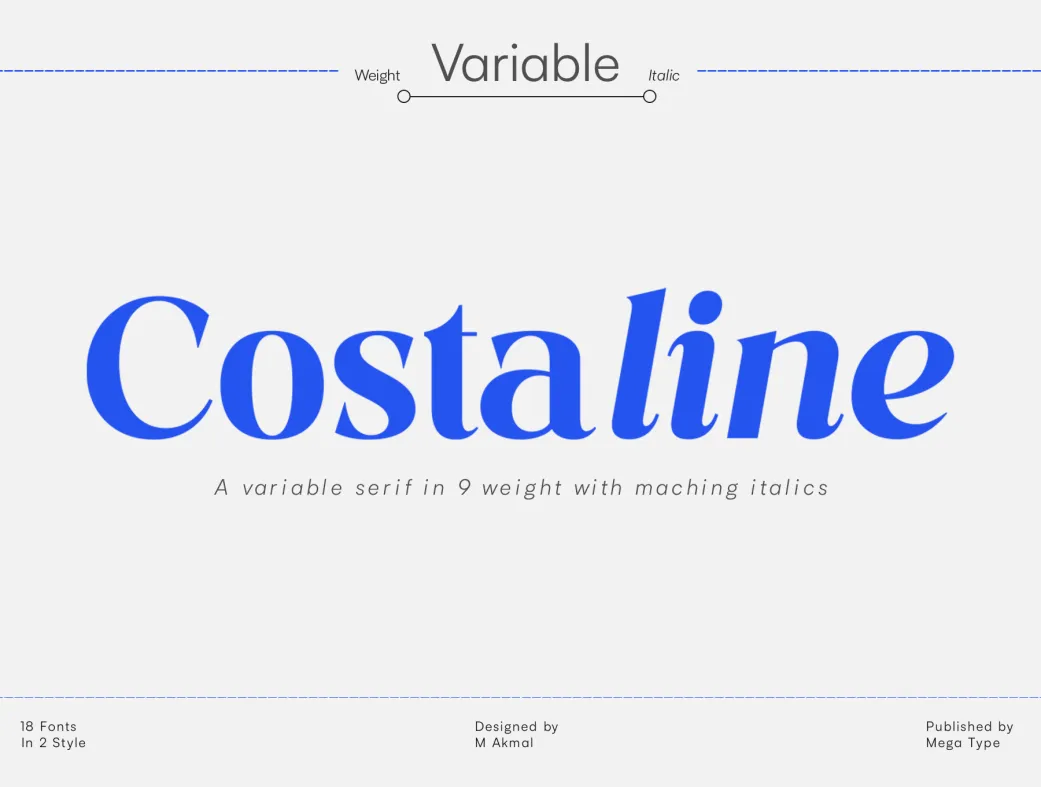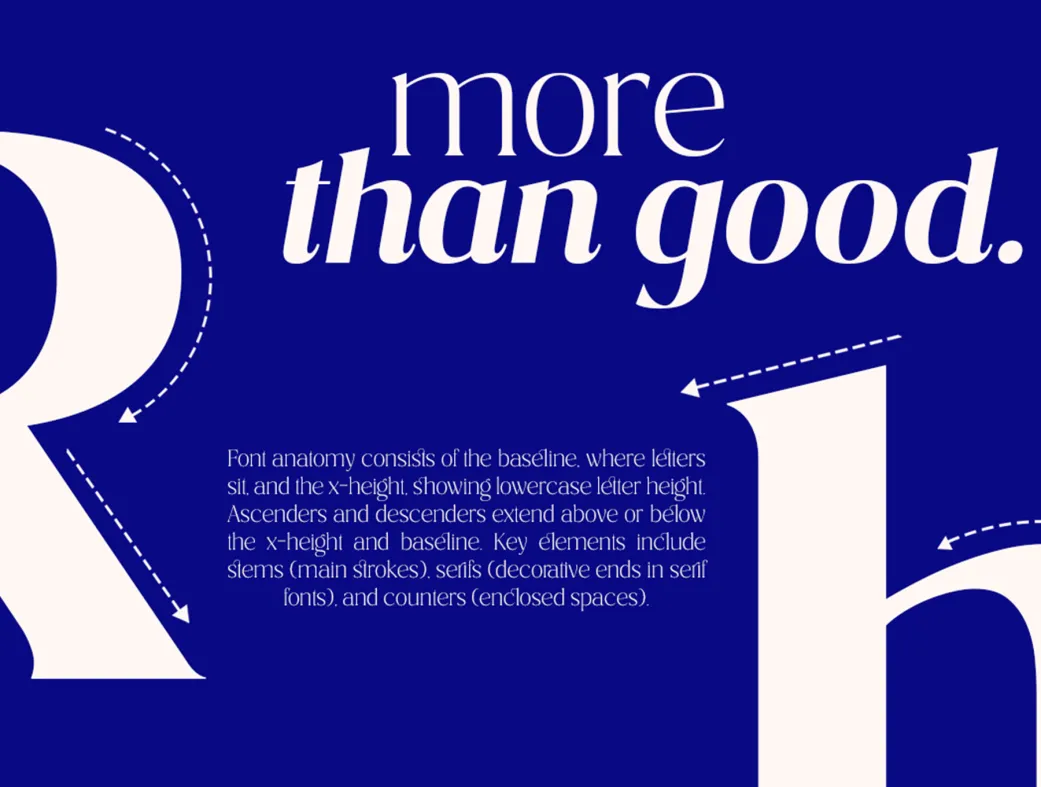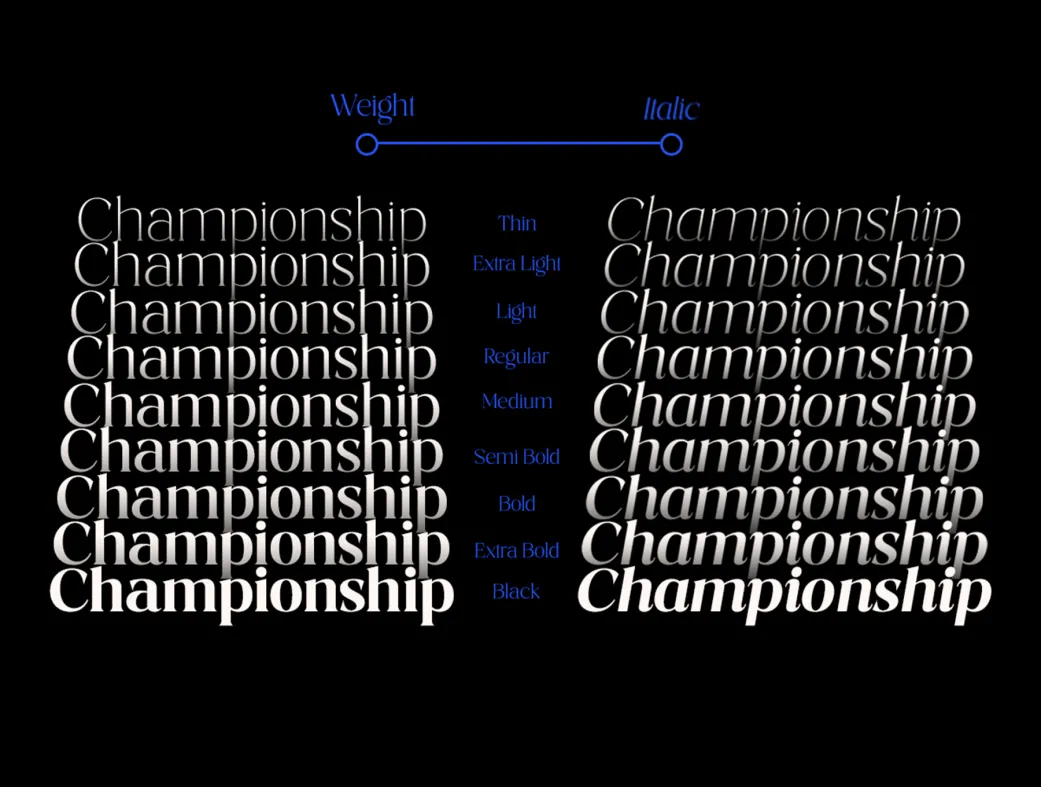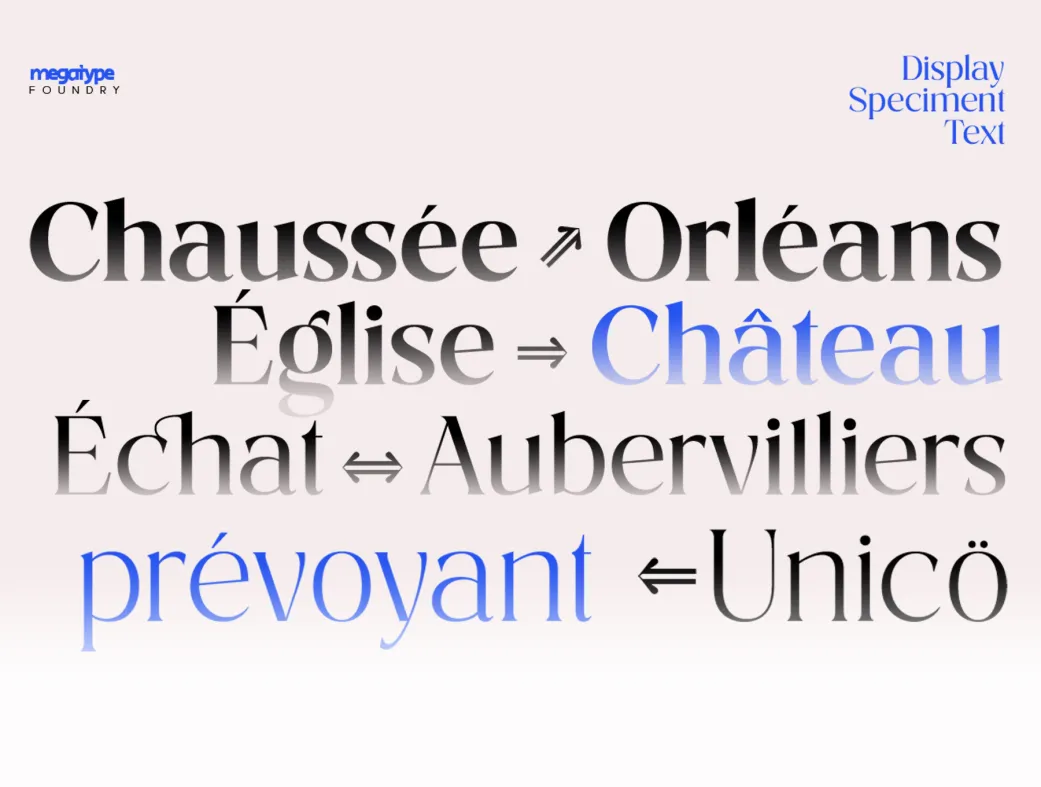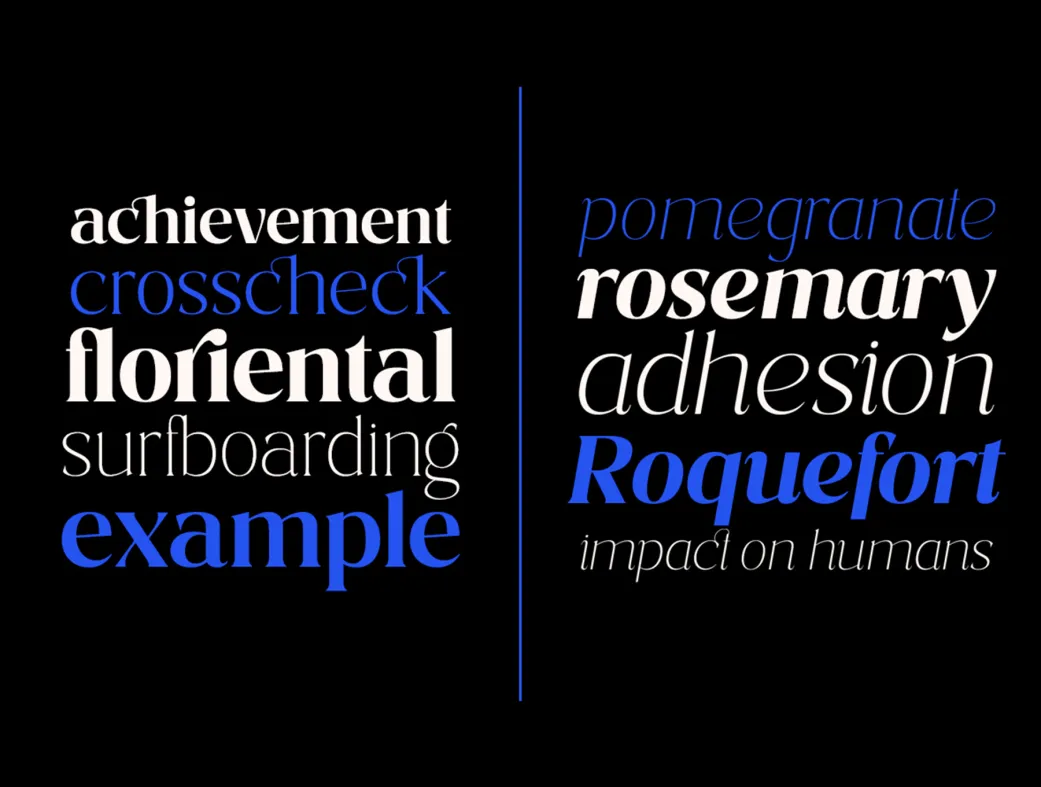
خانواده فونت کاستالین | Costaline
کاستالین، خانواده فونت سریف مدرن و جذاب با حس کلاسیک، ایده‌آل برای طراحی‌های شماست!
Costaline Font Family
خانواده فونت کاستالین | Costaline | Megatype
معرفی محصول:
خانواده فونت کستالین (Costaline) یک فونت سریف مدرن و هماهنگ است که حس کلاسیک را به زیبایی در خود جای داده است. این مجموعه شامل ۱۸ فونت با وزن‌های مختلف از نازک تا سیاه می‌باشد که در دو حالت راست و ایتالیک ارائه می‌شود. کستالین با منحنی‌های طبیعی و ساقه‌های پف‌دار، به طرز جذابی با افزایش وزن، شکل و شخصیت خود را به نمایش می‌گذارد.
ویژگی‌ها و مزایا:
کاستالین با داشتن وزن‌های نازک، کنتراست کاهش‌یافته و اصلاحات اپتیکی، ظاهری گرم و نرم ایجاد می‌کند. این فونت همچنین دارای ایتالیک‌های زیبا با وزن‌های کاملاً متناسب است که می‌تواند به طراحی‌های شما جلوه خاصی ببخشد. امکانات OpenType این فونت به طراحان اجازه می‌دهد تا از ویژگی‌هایی مانند لیگاتورها بهره‌برداری کرده و از چندین زبان پشتیبانی کند.
کاستالین همچنین با دو نسخه متغیر Regular و Italic ارائه می‌شود که به طراحان این امکان را می‌دهد تا به راحتی در طراحی‌های خود کاوش کرده و جزئیات بصری و رازهای پنهان بسیاری را کشف کنند. این فونت گزینه‌ای عالی برای پروژه‌های طراحی مختلف از جمله طراحی ویرایشی، عناوین، پروژه‌های برندینگ، طراحی لوگو، بسته‌بندی، عناوین مجله، تبلیغات و متن‌های کوتاه یا بلند و طراحی وب است.
کاربردها و نکات استفاده:
برای طراحان حرفه‌ای: کستالین می‌تواند به عنوان یک انتخاب ایده‌آل برای ایجاد هویت برند شما، طراحی پوسترها و یا ایجاد عناوین جذاب در مجلات مورد استفاده قرار گیرد.
سوالات متداول:
1. آیا خانواده فونت کاستالین شامل وزن‌های مختلف است؟
بله، این خانواده شامل ۱۸ فونت با وزن‌های نازک تا سیاه است.
2. آیا فونت کاستالین از چند زبان پشتیبانی می‌کند؟
بله، این فونت از چندین زبان پشتیبانی می‌کند و امکانات OpenType آن به شما این امکان را می‌دهد که از لیگاتورها استفاده کنید.
3. آیا می‌توان از کاستالین برای طراحی وب استفاده کرد؟
بله، کستالین گزینه‌ای عالی برای طراحی وب و سایر پروژه‌های دیجیتال است.
5. آیا فونت کاستالین دارای نسخه‌های متغیر است؟
بله، کستالین با دو نسخه متغیر Regular و Italic عرضه می‌شود که به طراحان کمک می‌کند تا طراحی‌های خود را به راحتی ویرایش کنند.